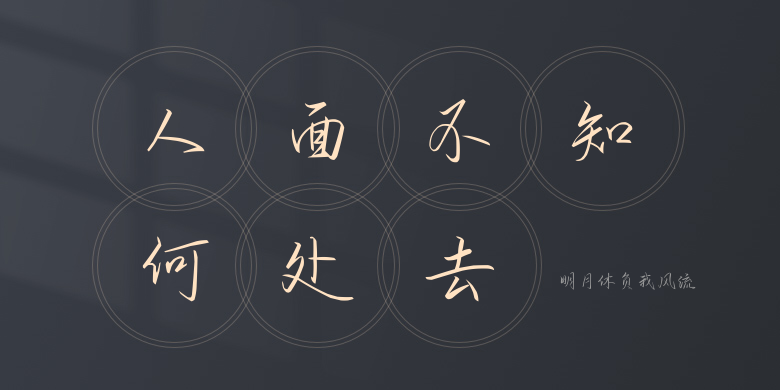
明月休负我风流
明月休负我风流,这款字体结构工整、笔画清晰,兼顾美观与易读性,适用于标题、正文、海报、包装、LOGO 等多种场景。字形优雅稳定,风格百搭耐看,适配日常排版与创意设计,让文字呈现更舒适、更具质感。明月休负我风流一笔一画,皆是细节,以均衡的比例、流畅的线条打造舒适视觉体验,字形端正大气,风格简约现代。无论是商业设计、品牌宣传还是日常排版,都能轻松驾驭,让文字更有格调与力量。明月休负我风流字体下载。